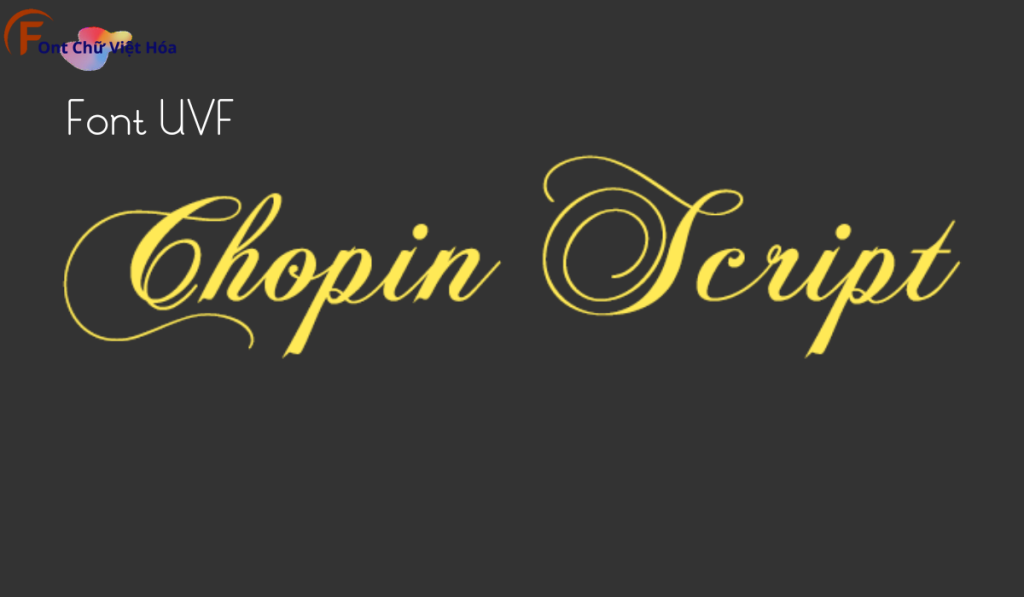
Fonts UVF Chopinscript Việt Hóa
Bộ Font: UVF
Phân loại: Cá tính, độc đáo
Kiểu chữ: Chữ thảo
UVF Chopinscript Việt Hóa là font chữ thảo với các đường nét mềm mại và tinh tế, thuộc bộ font UVF. Font này được thiết kế nhằm mục tiêu tạo ra sự thanh lịch và dễ đọc, đặc biệt phù hợp cho các thiết kế như thiệp mời, poster, và logo. Đặc điểm hình dạng của UVF Chopinscript là các đường nét uốn lượn và tỷ lệ chữ cân đối, giúp tạo ấn tượng thị giác mạnh mẽ. Font này cũng đã được Việt hóa, mang đến sự linh hoạt và tiện dụng cho các dự án thiết kế bằng tiếng Việt, giúp người dùng dễ dàng tiếp cận và sử dụng.